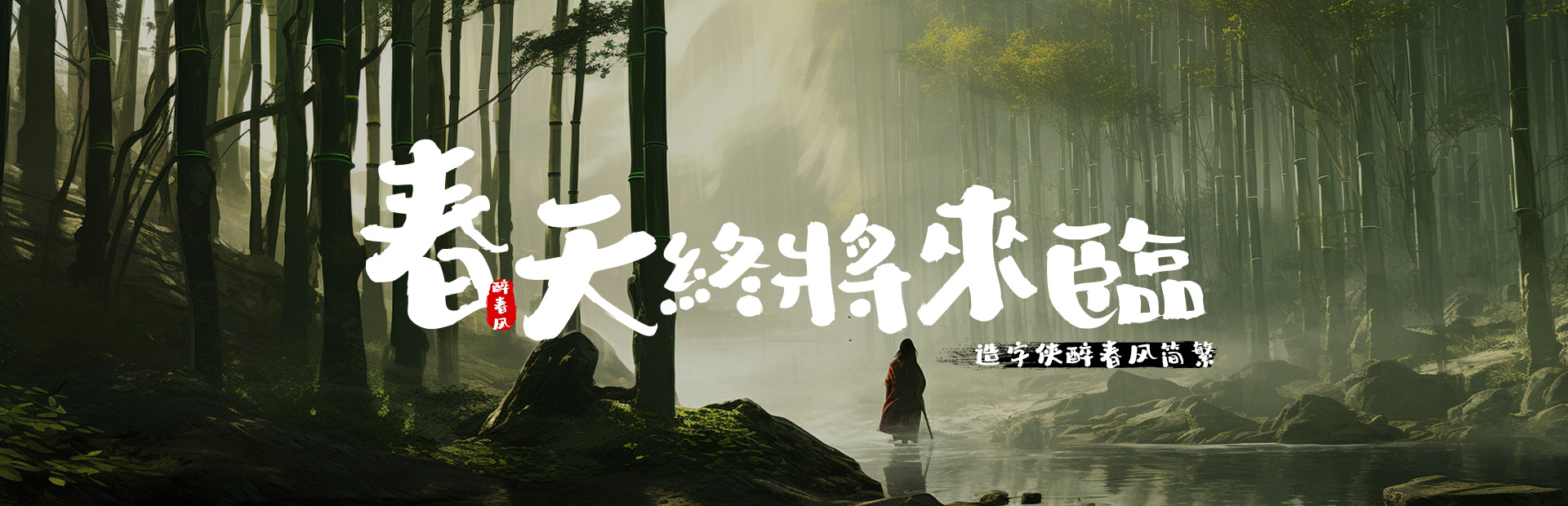
醉春风,自由之歌轻轻唱
醉春风,自由之歌轻轻唱。让心随风舞,身随云翔,无拘无束,畅游天地广。春风拂面,暖意融融,心中喜悦,如诗如画,自由之梦,随风飘荡。
造字侠醉春风简繁 苍劲 整体风格呈现出自由率真、活泼灵动之感,单字结构周正不失松弛,点画圆润,笔画间粗细过度自然,再者灵动的笔画走势造就独特字形风貌。
醉春风,自由之歌轻轻唱。让心随风舞,身随云翔,无拘无束,畅游天地广。春风拂面,暖意融融,心中喜悦,如诗如画,自由之梦,随风飘荡。
造字侠醉春风简繁 苍劲 整体风格呈现出自由率真、活泼灵动之感,单字结构周正不失松弛,点画圆润,笔画间粗细过度自然,再者灵动的笔画走势造就独特字形风貌。